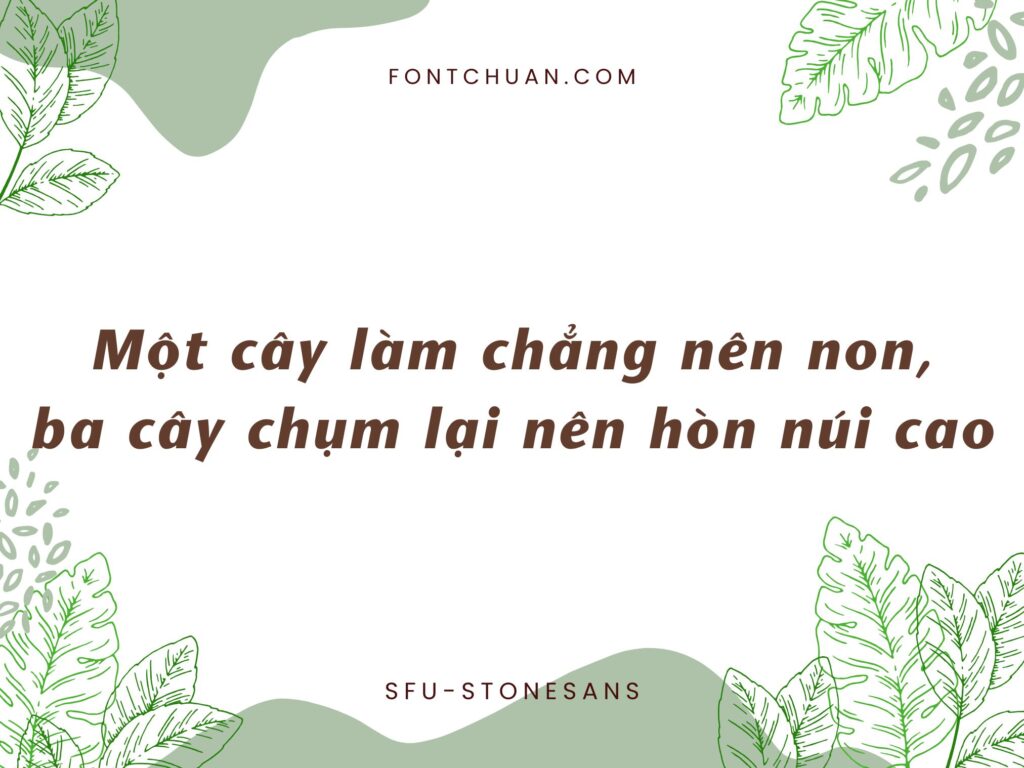
Font SFU Stonesans Việt Hóa
Font SFU Stone Sans là một kiểu chữ sans-serif hiện đại, được thiết kế với các đường nét rõ ràng và cân đối, tạo cảm giác chuyên nghiệp và dễ đọc. Font này bao gồm nhiều biến thể như Regular, Italic, Bold, Bold Italic, Semi Bold Regular và Semi Bold Italic, mang lại sự linh hoạt cho các dự án thiết kế khác nhau.
SFU Stone Sans lý tưởng cho các dự án thiết kế logo, tiêu đề, bao bì sản phẩm và các ấn phẩm quảng cáo. Các ngành nghề như quảng cáo, giáo dục và công nghệ có thể tận dụng font này để tạo điểm nhấn trong thiết kế. Ngoài ra, font cũng thích hợp cho các sự kiện như Tết, Giáng sinh, Valentine và các lễ hội khác.